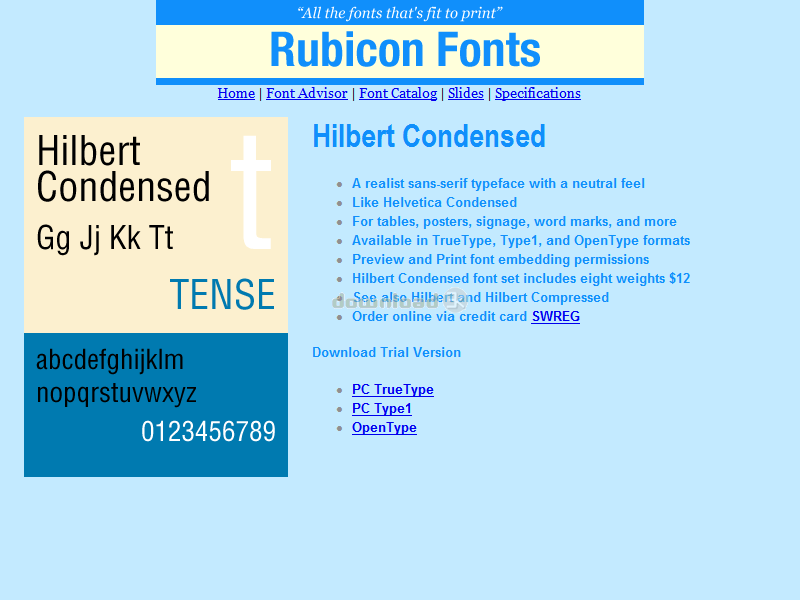
"Реалист шрифт без засечек, нейтральные чувства"
Сокращенный реалист шрифт без засечек с нейтральным чувствую. Как Helvetica Condensed. Ненавязчивый шрифтом, что, кажется, всюду. Установите более текста в ограниченном пространстве без потери четкости. Отлично подходит для таблиц, плакатов, вывесок и других графических материалов. Точная и намекнул, соответствующий шрифт метрик, стандартный набор символов, кернинг пар. Профессиональное качество печати на струйных, лазерных, наборщик до 3500 точек на дюйм. Покупатели получают 8 вариантов шрифта следующим образом: свет, свет Oblique, Normal, Oblique, Bold, Bold Oblique, ExtraBold, ExtraBold Oblique.Требования: No special requirements.